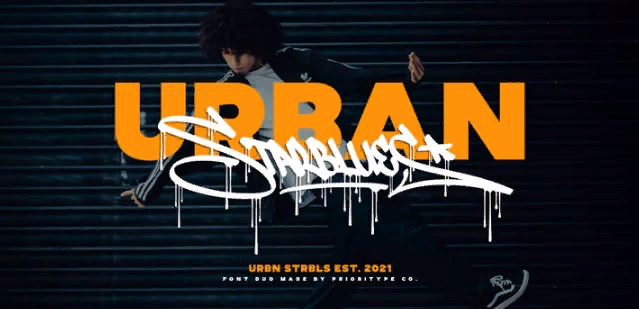
Сильные парные шрифты в качестве основного отображения дизайна.
Да, он очень хорошо подходит для дизайна на тему граффити.
Вы можете применить его для дизайна футболок, плакатов, обложек, миниатюр видео, товаров и так далее, чтобы придать им особый вид.
Особенности: Прописные, Строчные, (All Caps Sans) Цифры, Пунктуация, Многоязычный, Альтернативный (Граффити) & PUA Encoded.